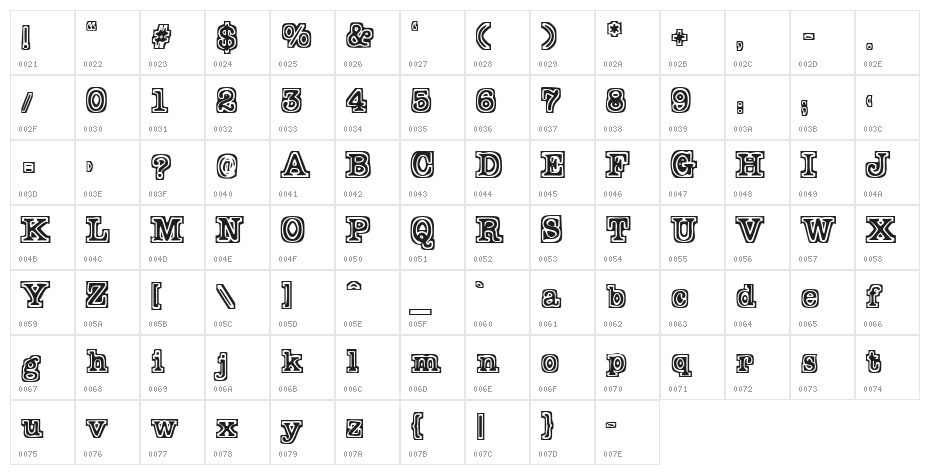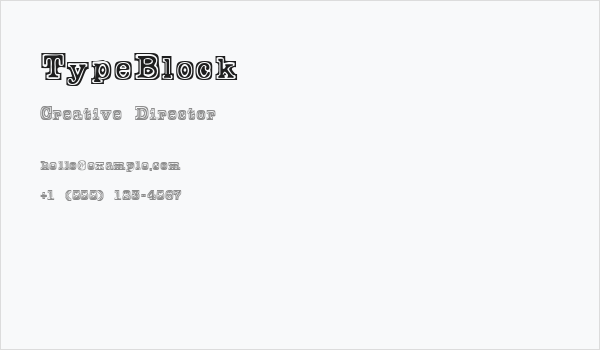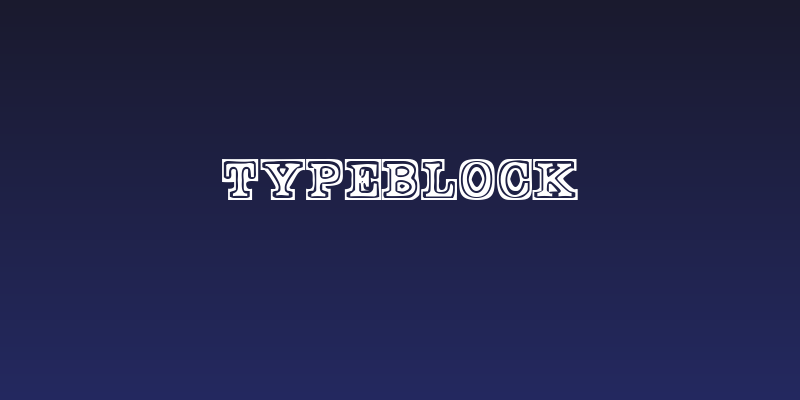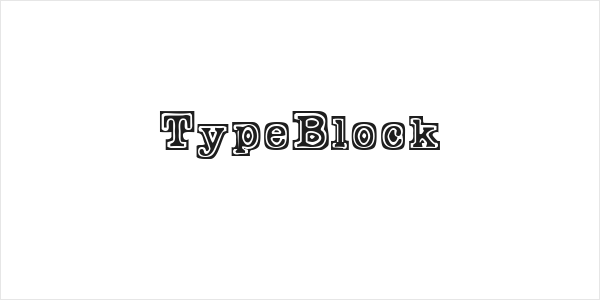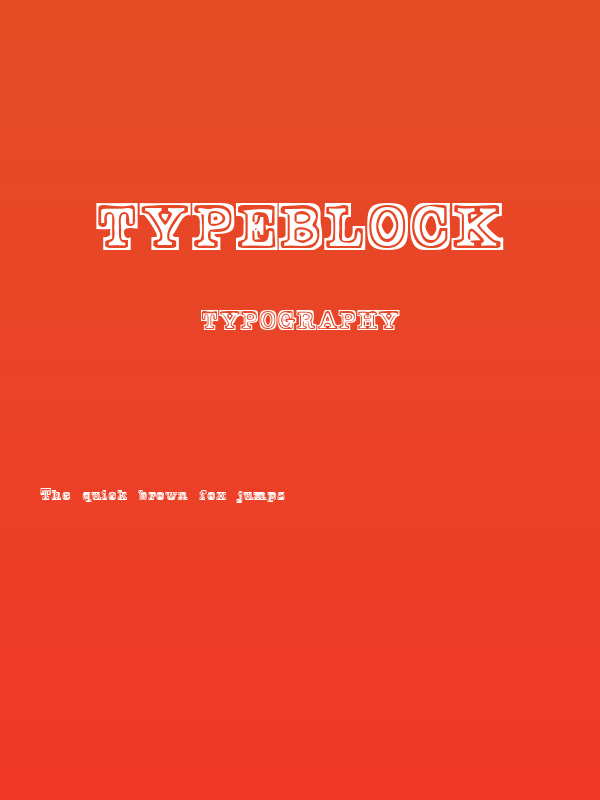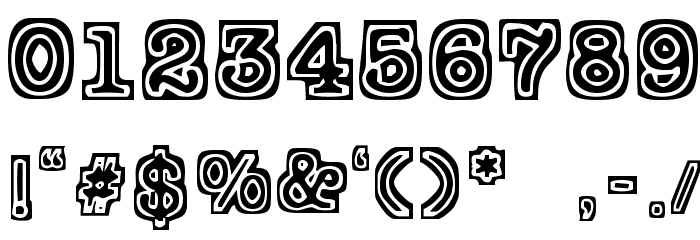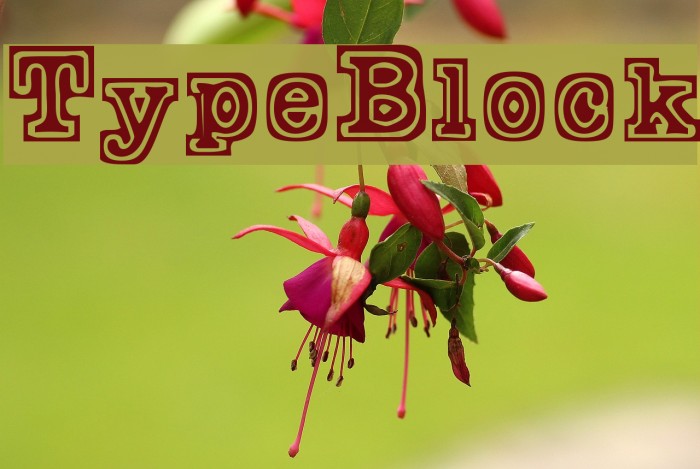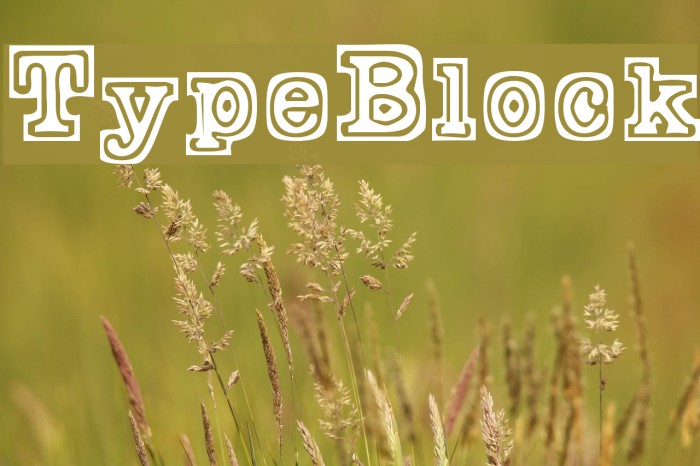
TypeBlock Font
| Gesamtstil | Vintage, Decorative |
| Vorgeschlagene Projekte | Ideal for posters, branding, headlines, and any design needing a retro or decorative touch. |